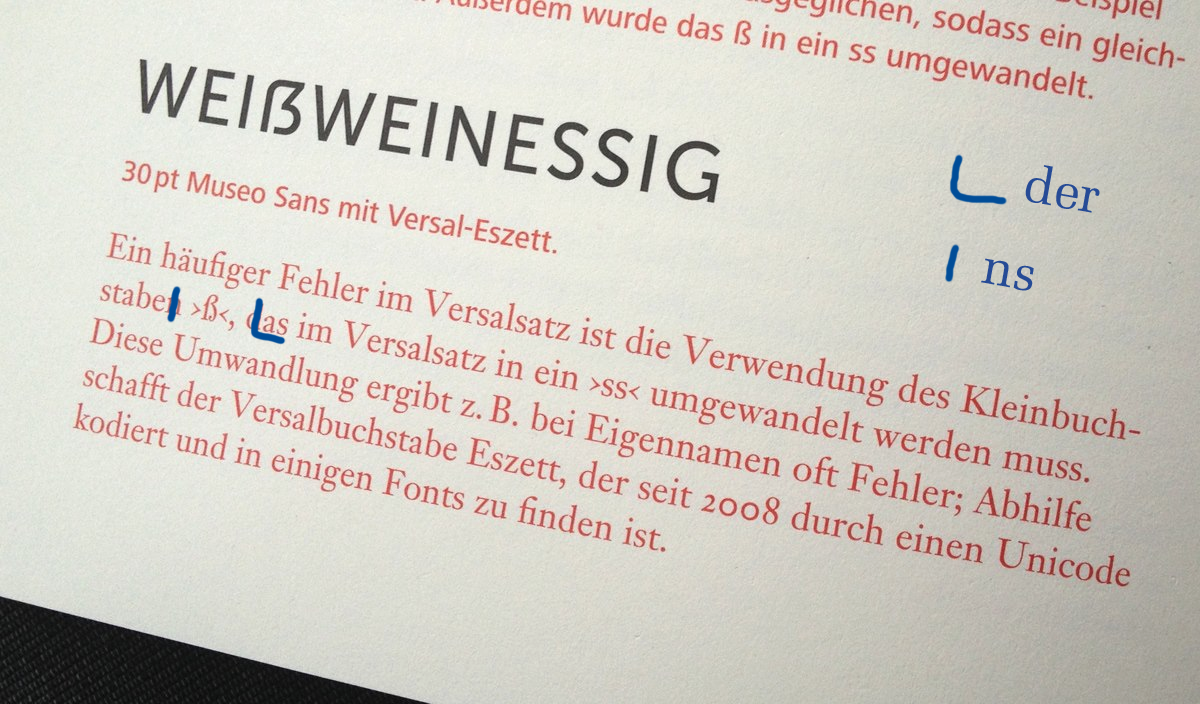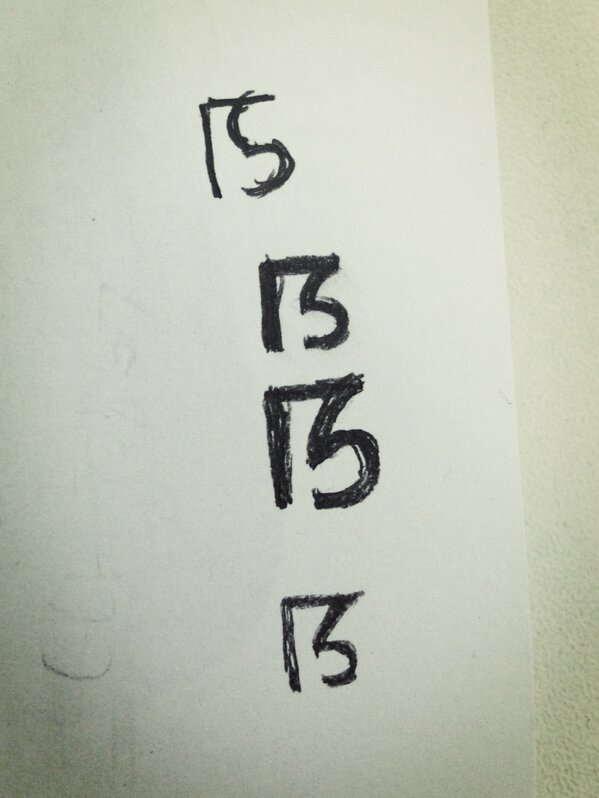
By the way: für mich ist Typografie.info ohne Versaleszett beinahe so wie Topf ohne Deckel;-)
Gibt es denn Bestrebungen das Forum noch diesbezüglich wieder zu »komplettieren«? Ist ja sowieso viel zu schade um die Tisa , dass man sie so stiefmütterlich behandelt ins Rennen geschickt hat.  :zzzz:
Gibt es denn Bestrebungen das Forum noch diesbezüglich wieder zu »komplettieren«?
Siehst du denn keines? Austerlitz hat doch nur einen Witz versucht und das vermeintliche Fehlen künstlich erzeugt.
Theoretisch sollte das so aussehen:
In der FF Ernestine ist es nativ drin. In der FF Tisa soll es prinzipiell durch den Font Stack aus einem Einzelzeichenfont nachgeladen werden. In meinen Browsern klappt das auch überall.
Fein, fein – hätte mich auch gewundert! Fällt auch gar nicht auf, dass es ein anderer Font ist. Ich sehe es! : ) Ist das schon die ganze Zeit drin? Mir war so, als wäre es mal, jedenfalls in der Beta-Version?, nicht zu sehen gewesen.
Ich habe gerade in einem Druck von 1734 ein Eszett als Großbuchstabe gefunden. Es handelt sich um den Namen Straßburg im Versalsatz. Das Eszett wird als Großbuchstabe ganz unkompliziert durch ein S ersetzt, vgl. Die Catholische Strassburger Bibel, ganz unten auf dem Titelblatt. Im gewöhnlichen Satz wurde Straßburg übrigens sehr wohl mit Eszett geschrieben, vgl. drei Zeilen weiter oben.
Ich habe gerade in einem Druck von 1734 ein Eszett als Großbuchstabe gefunden.
Ich seh nur ein S. Nur weil man an dieser Stelle im gemischten Satz ein Eszett erwartet, ist ja ein S im Versalsatz an dieser Stelle nicht automatisch ein Versal-Eszett. So wie die Übliche SS-Schreibung ja auch niemand als großes Eszett beschreibt.
Das Eszett wird als Großbuchstabe ganz unkompliziert durch ein S ersetzt, vgl. Die Catholische Strassburger Bibel, ganz unten auf dem Titelblatt. Im gewöhnlichen Satz wurde Straßburg übrigens sehr wohl mit Eszett geschrieben, vgl. drei Zeilen weiter oben.
Nach nur wenigen Weglassungen kann man aus austerlitz’ Zeilen durchaus ebenso lesen, dass es ihm möglicherweise gefällt, dass man 1734 die versalige SS-Welt noch nicht sooo scharf sah.
Der Duden ist immer noch nicht so weit. Im neuen Newsletter heißt es: »Soll ein Wort, das ein ß enthält, in Großbuchstaben geschrieben werden, wird ß durch ss ersetzt: STRASSE«, im ganzen Newsletter kann ich keinen Hinweis für die Existenz des versalen ß finden.
»Die internationale Organisation für Normung (ISO) hat nun in den internationalen Zeichensätzen ISO-10646 und Unicode 5.1 ein Zeichen für das große Eszett festgeschrieben: eine wichtige Neuerung, besonders für Buch- und Zeitungsverlage, aber eine, die nicht Bestandteil der amtlichen Rechtschreibung ist. Allerdings darf mündigen Bürgerinnen und Bürgern im Einzelfall getrost die Entscheidung überlassen werden, ob sie das große Eszett etwa für die Schreibung ihres Namens nutzen oder nicht.«
Das klingt ja noch nicht sehr ambitioniert …
Schon klar. Ich bezog mich insbesondere auf: »aber eine, die nicht Bestandteil der amtlichen Rechtschreibung ist.«  ;-)  Irgendwie klang das für mich gestern Abend mehr nach einer Info, dass es das VE jetzt zwar offiziell gibt, aber das war es eben auch schon.
Aber für das jetzige Stadium, ist das schon in Ordnung. Und sollte sich die Anwendung des VE irgendwann einmal etablieren, kann ja auch noch mehr daraus werden …
Und nach nochmaligen lesen, ist ja doch eine subtile Werbetrommel zu hören.  :roll:
:tuschel:  Für alle, die interessiert um welches Buch es sich genau handelt:
Schrift wirkt, Jim Williams und Gesine Hildebrandt
Immer erst an die eigene Nase fassen, liebe Schmidts!
Wenn du das als "brüsten" ansiehst … allein schon die Behauptung, das ss führe bei Eigennamen oft zu Fehlern, und die einzig korrekte Abhilfe schaffe nur das Versal-Eszett, ist einfach falsch. Dass das keinem auffiel, wundert mich. Mal abgesehen von den grammatischen Fehlern. Und das Versal-Ezett ist doch Thema des Strangs, oder nicht?
Ich trete auch gern den Gegenbeweis an: Mein Nachname Weiß wird zu WEISS, der einzig richtigen versalen Schreibweise. Es sind und bleiben einfach nur Geschmäcker, die hier aufeinandertreffen. Objektive Argumente gab und gibt es keine.
Mein Nachname Weiß wird zu WEISS, der einzig richtigen versalen Schreibweise.
Steht ja auch da. » … das im Versalsatz in SS umgewandelt werden muss.«
… allein schon die Behauptung, das ss führe bei Eigennamen oft zu Fehlern, und die einzig korrekte Abhilfe schaffe nur das Versal-Eszett, ist einfach falsch … Es sind und bleiben einfach nur Geschmäcker, die hier aufeinandertreffen. Objektive Argumente gab und gibt es keine.
der einzig richtigen versalen Schreibweise
Wenn ich den Duden richtig verstanden habe, ist auch dies nur eine Frage des »Geschmacks«. Von richtig oder falsch ist dort jedenfalls nicht mehr die Rede:
»Allerdings darf mündigen Bürgerinnen und Bürgern im Einzelfall getrost die Entscheidung überlassen werden, ob sie das große Eszett etwa für die Schreibung ihres Namens nutzen oder nicht.«